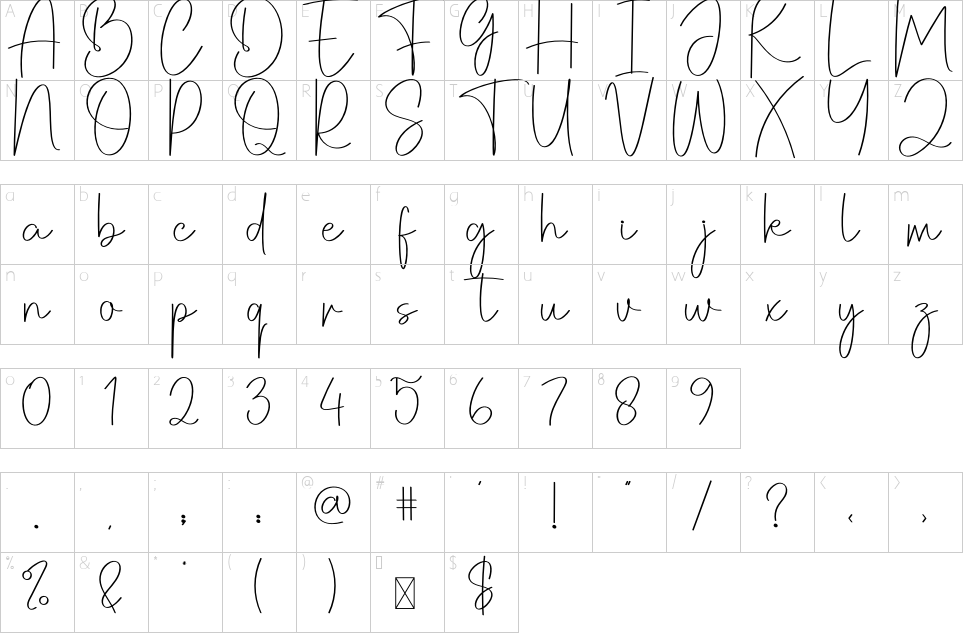
Awesome Signature Font – Download Grátis
Descubra a fonte “Awesome Signature Font” para Windows e Mac. Esta fonte foi projetada por scratchones, um designer talentoso. Com seu design elegante e elegante, a “Awesome Signature Font” é perfeita para criar assinaturas memoráveis e gráficos atraentes. Com mais de 900 downloads, é evidente que muitos designers concordam sobre seu valor. Adquira-a gratuitamente para adicionar um toque único e pessoal a seus projetos. Não perca essa oportunidade de adquirir uma fonte de alta qualidade que vai agradar os teus seguidores e clientes.